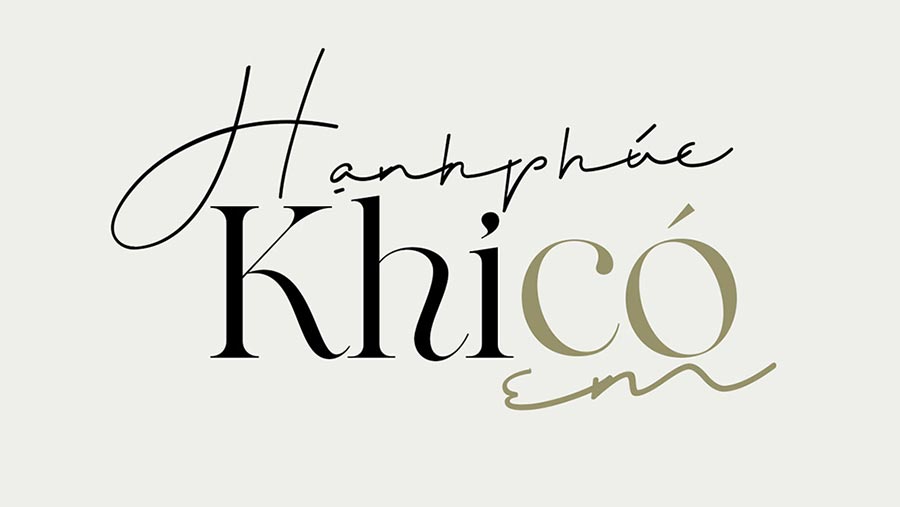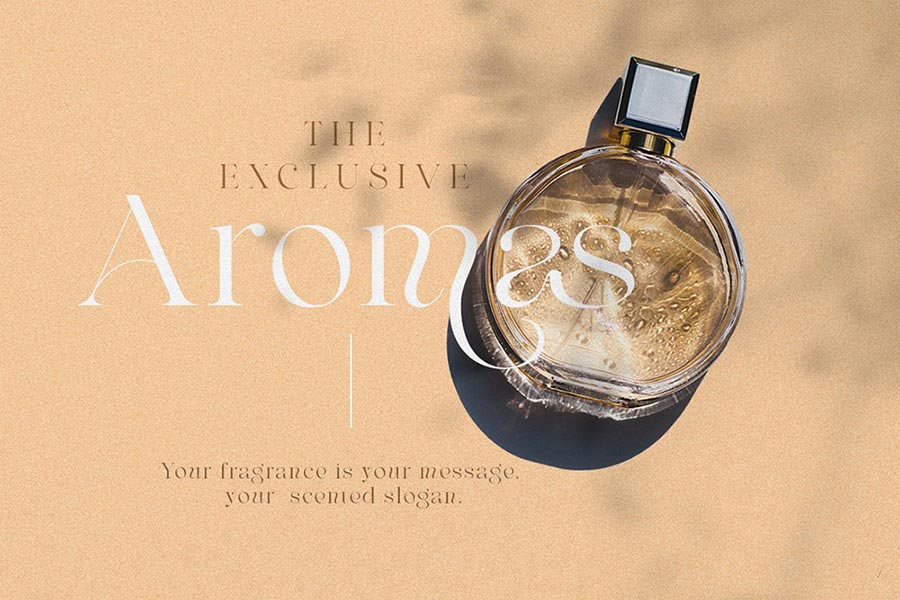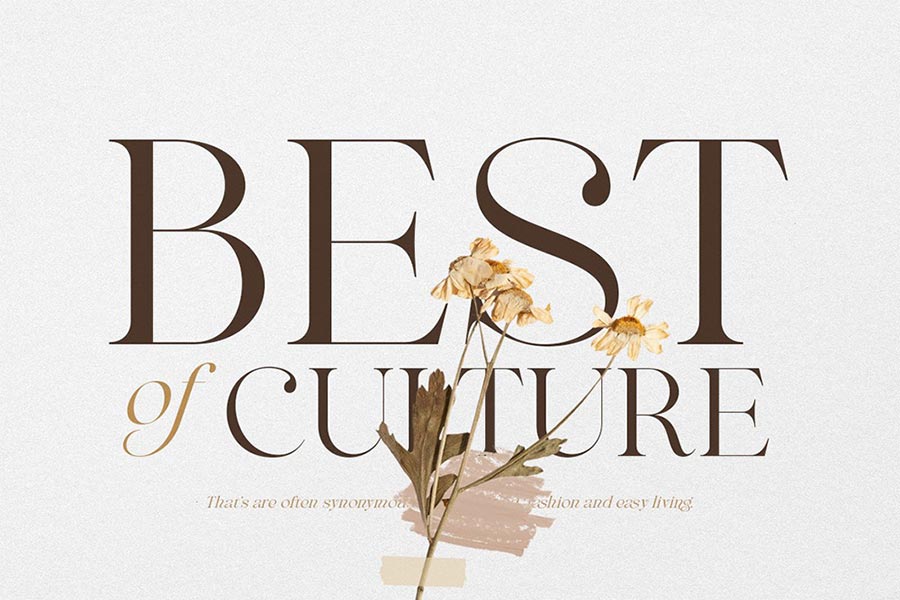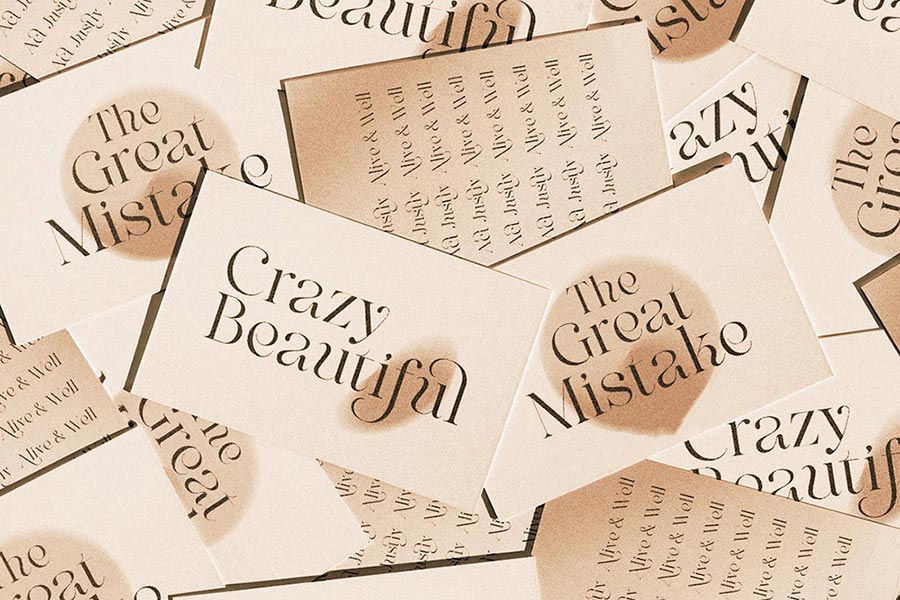
Chia Sẻ Miễn Phí Font Việt Hóa - Maglite Mang Phong Cách Hiện Đại Và Mượt Mà
Sự phát triển không ngừng của ngành thiết kế đồ họa và sáng tạo nội dung đã tạo nên nhu cầu lớn về các font chữ chất lượng cao, đặc biệt là các font Việt hóa. Trong bối cảnh đó, sadesign.vn đã trở thành một điểm đến quen thuộc cho cộng đồng thiết kế tại Việt Nam nhờ việc chia sẻ miễn phí nhiều font chữ độc đáo và hữu ích. Một trong những font nổi bật được giới thiệu gần đây chính là Maglite, một font mang phong cách hiện đại và mượt mà, phù hợp với nhiều dự án sáng tạo khác nhau.
2. Hỗ trợ tiếng Việt đầy đủ: Font Maglite và các font khác trên sadesign.vn đều hỗ trợ đầy đủ dấu câu và ký tự tiếng Việt, giúp người dùng dễ dàng ứng dụng trong các dự án bản địa hóa.
Ứng Dụng Font Maglite Trong Các Dự Án Thiết Kế
Font Maglite mang đến sự linh hoạt và tính ứng dụng cao trong nhiều loại dự án khác nhau. Dưới đây là một số gợi ý để tận dụng tối đa tiềm năng của font chữ này:
- Thiết kế nhận diện thương hiệu.
- Poster và banner quảng cáo.
- Thiết kế website.
- Ấn phẩm in ấn.
Sadesign Chia Sẻ Miễn Phí Font Việt Hóa - Maglite Mang Phong Cách Hiện Đại Và Mượt Mà:
Font Maglite là một lựa chọn tuyệt vời cho những ai đang tìm kiếm sự kết hợp giữa tính hiện đại và mềm mại trong thiết kế. Được Việt hóa bởi sadesign.vn, font chữ này không chỉ đáp ứng tốt nhu cầu sáng tạo mà còn mang lại giá trị sử dụng cao cho cộng đồng thiết kế tại Việt Nam.